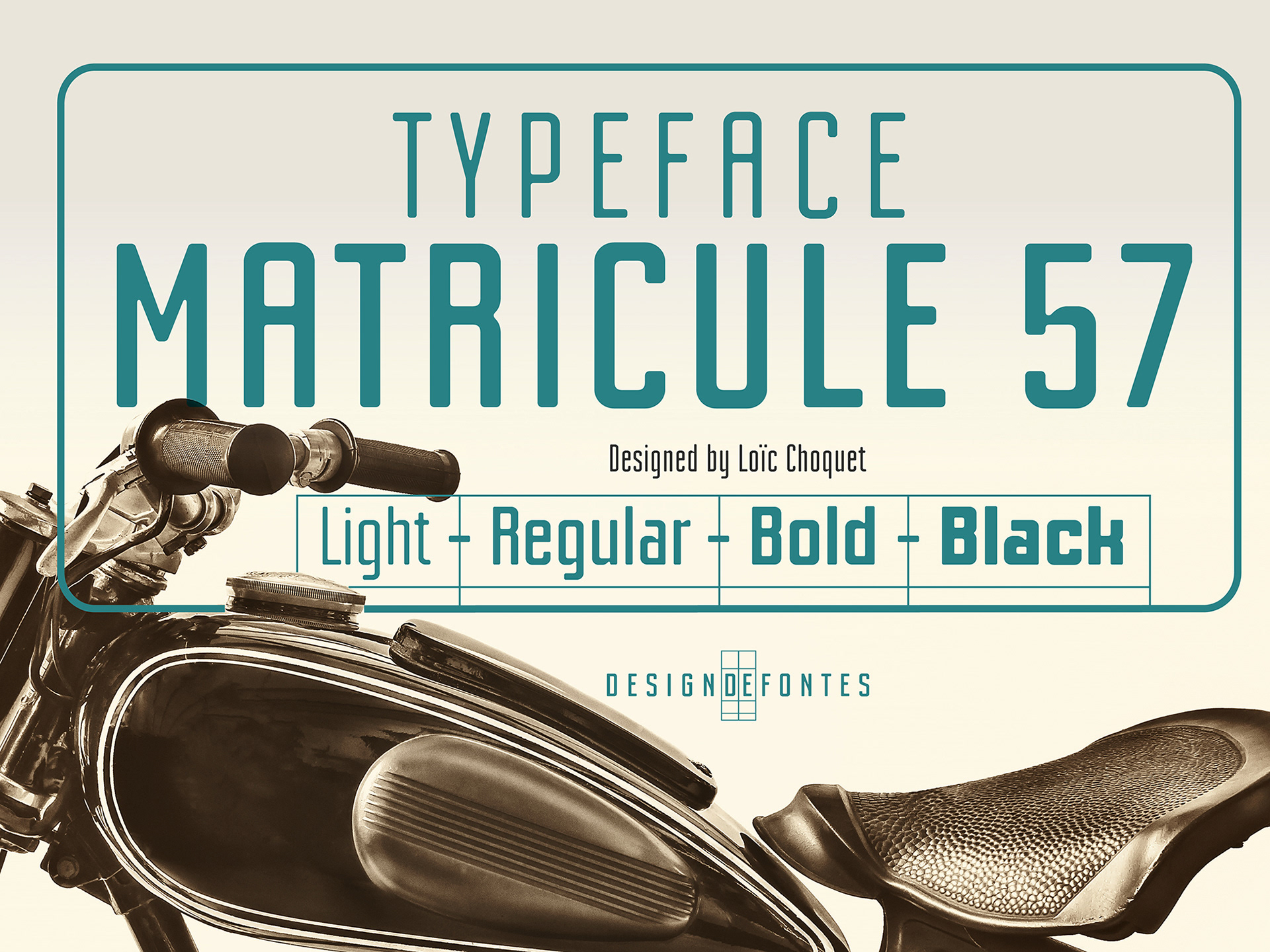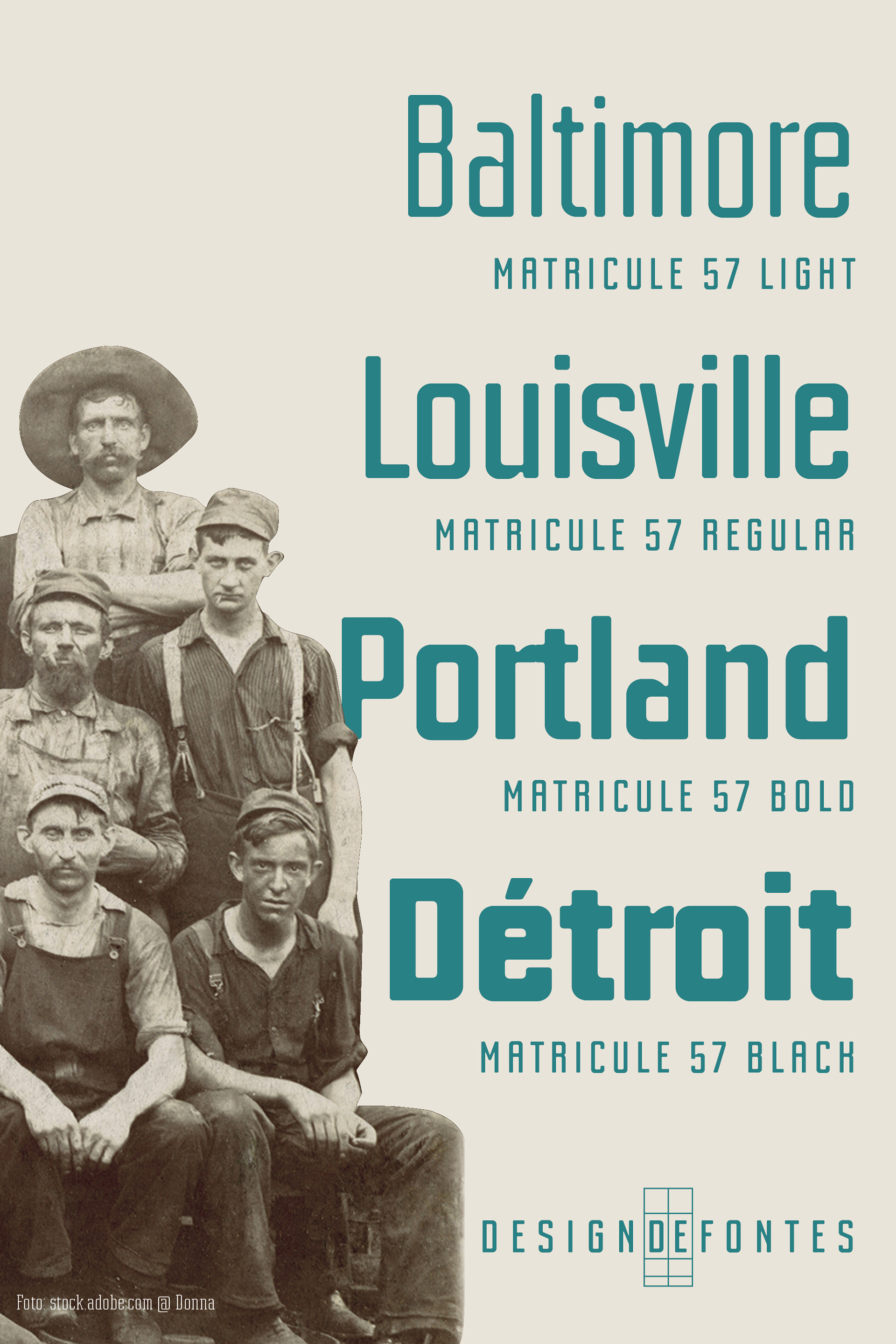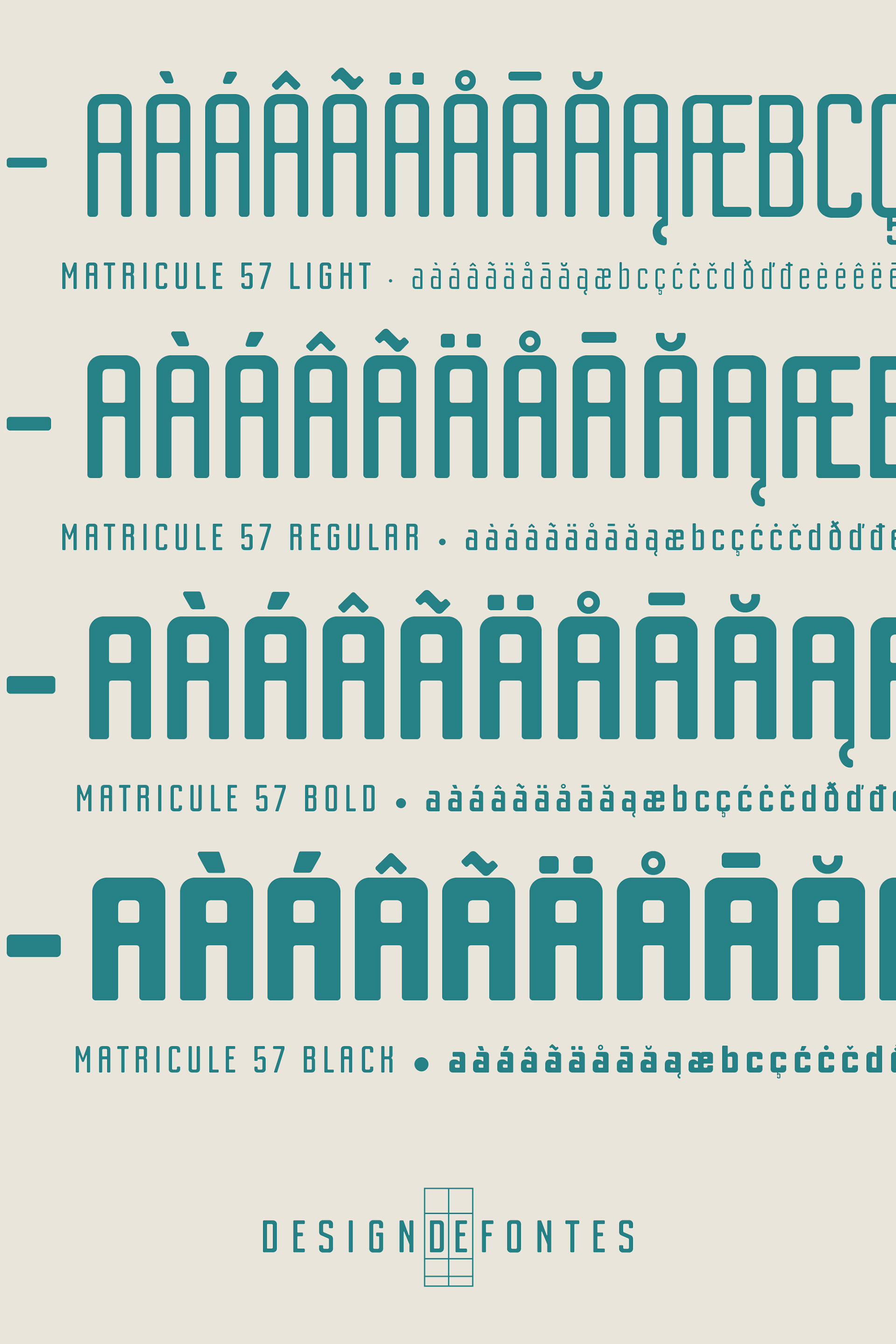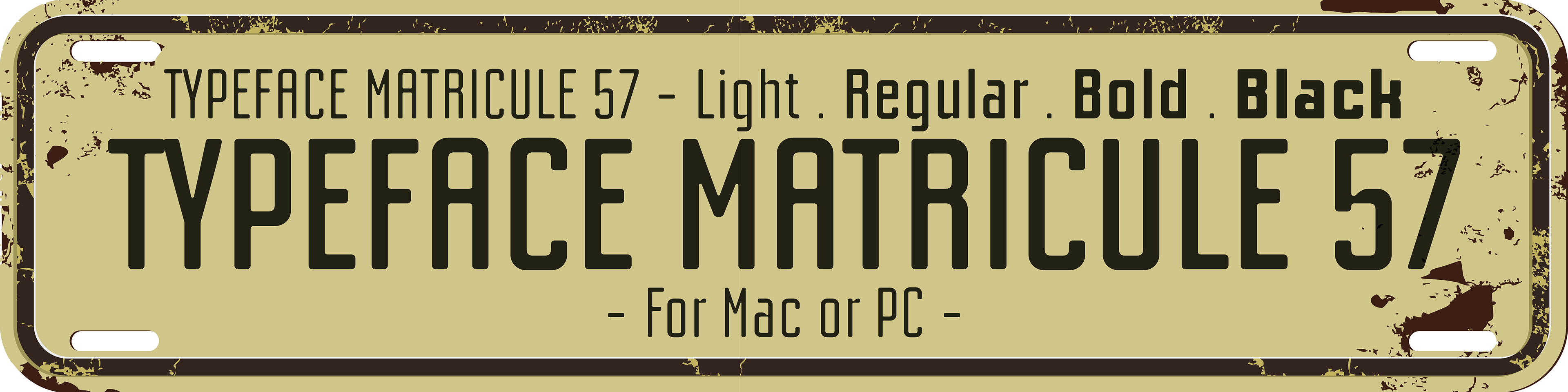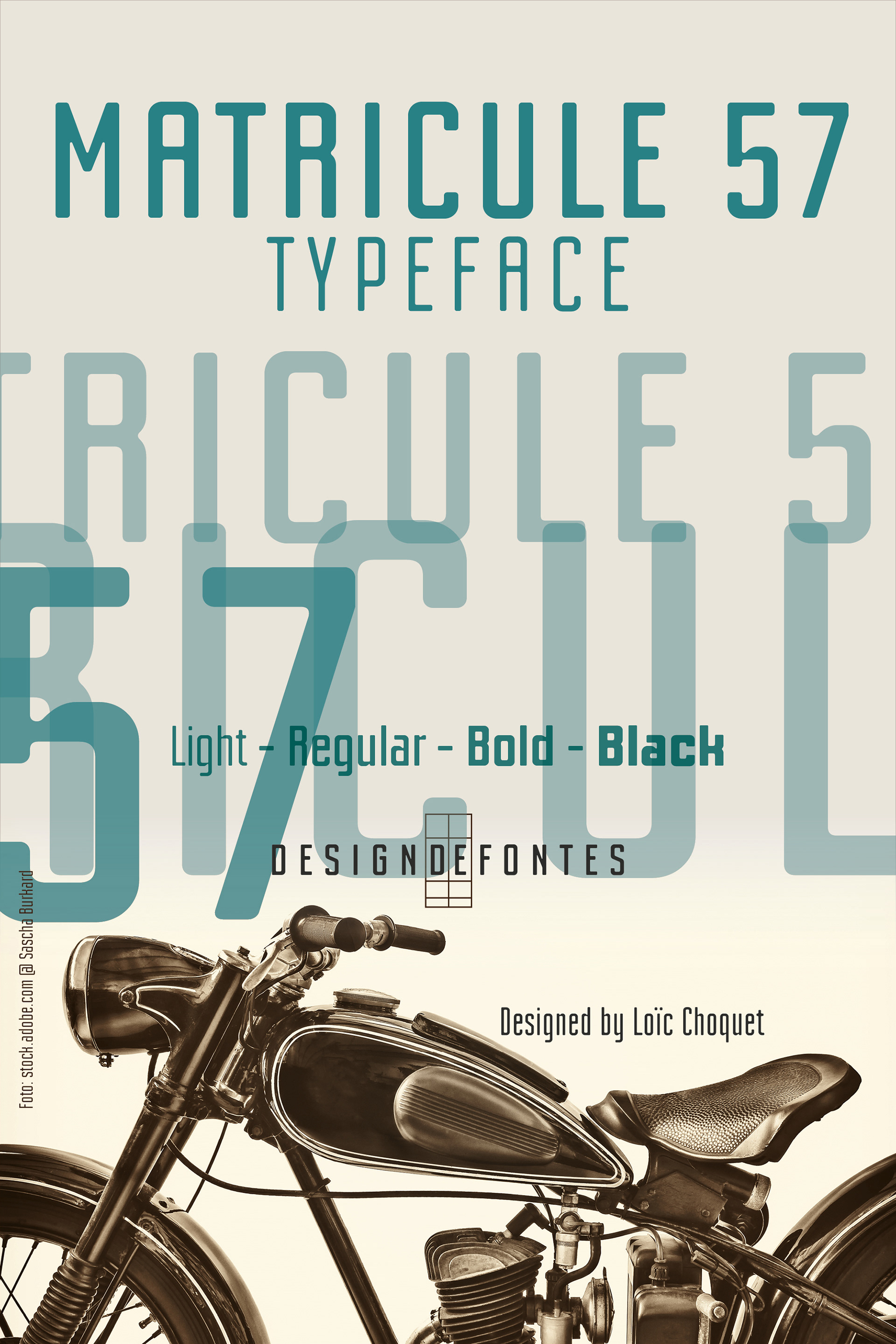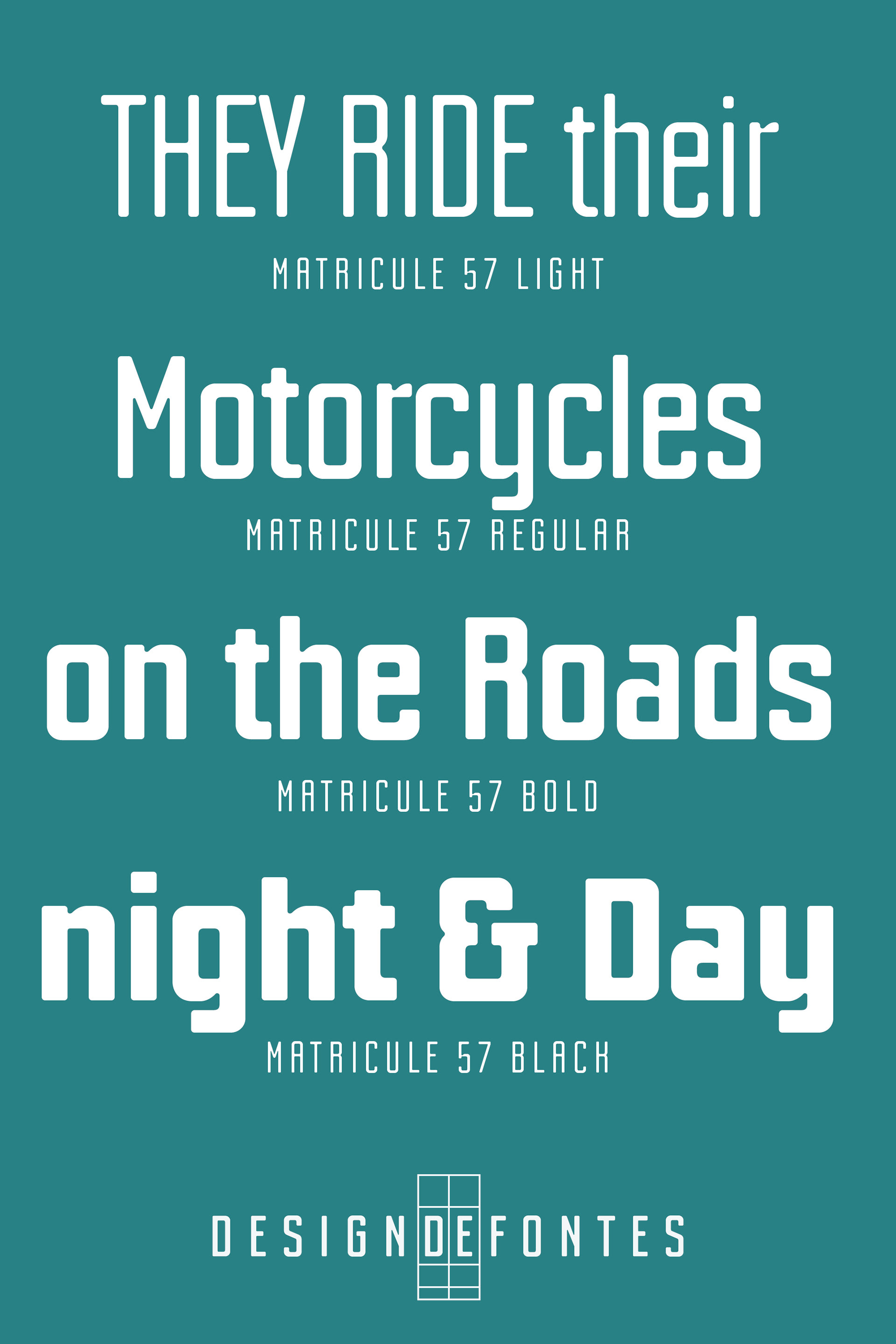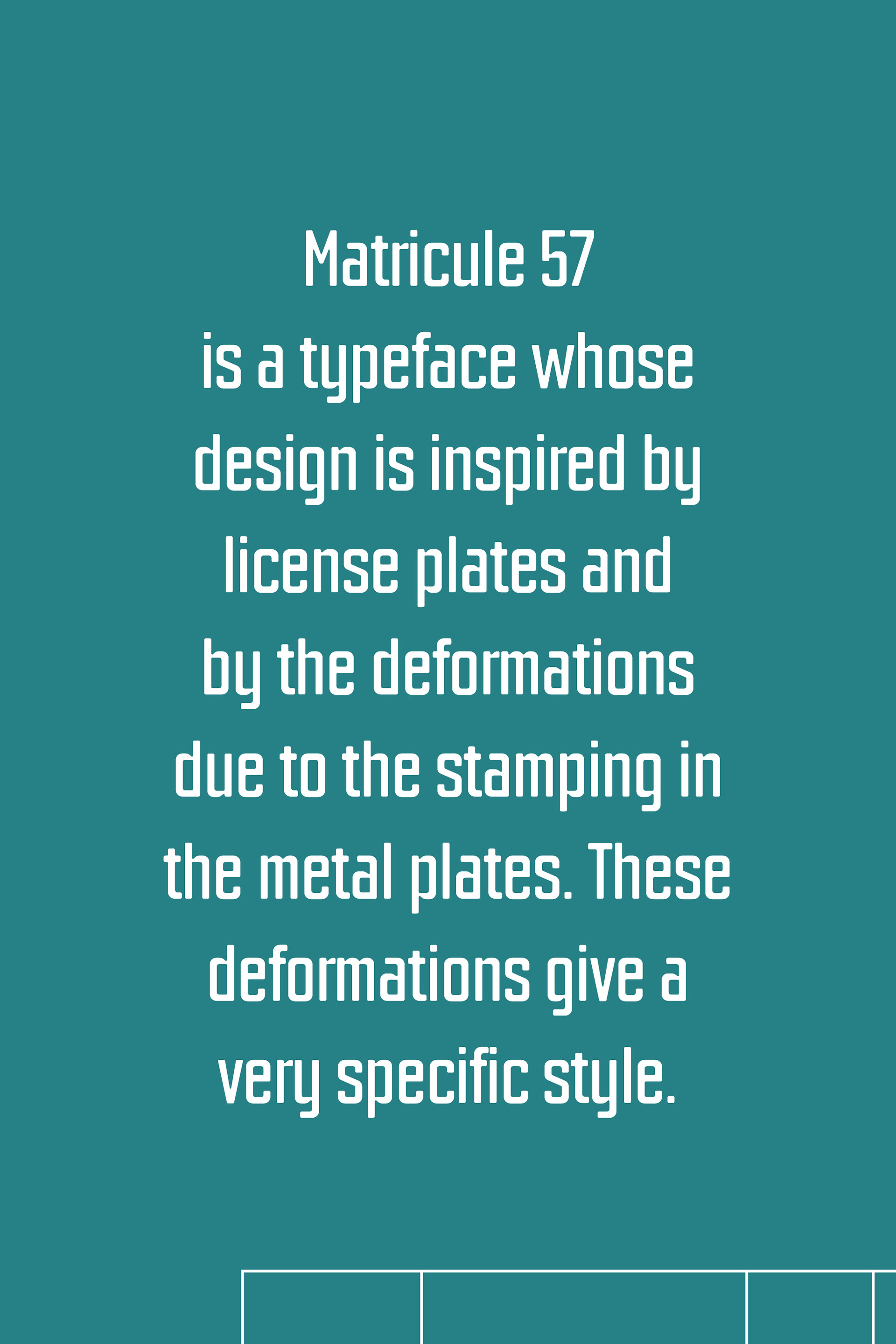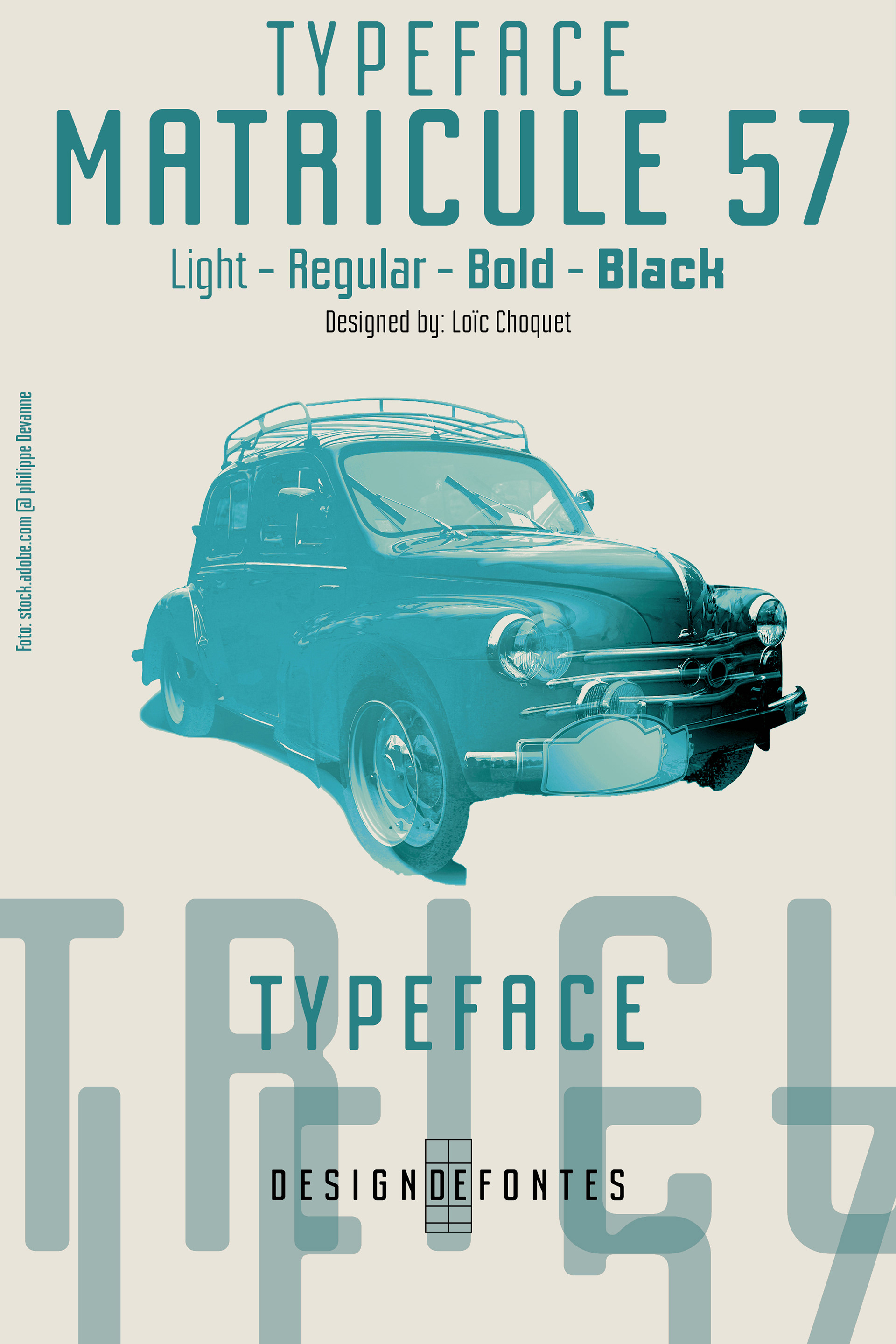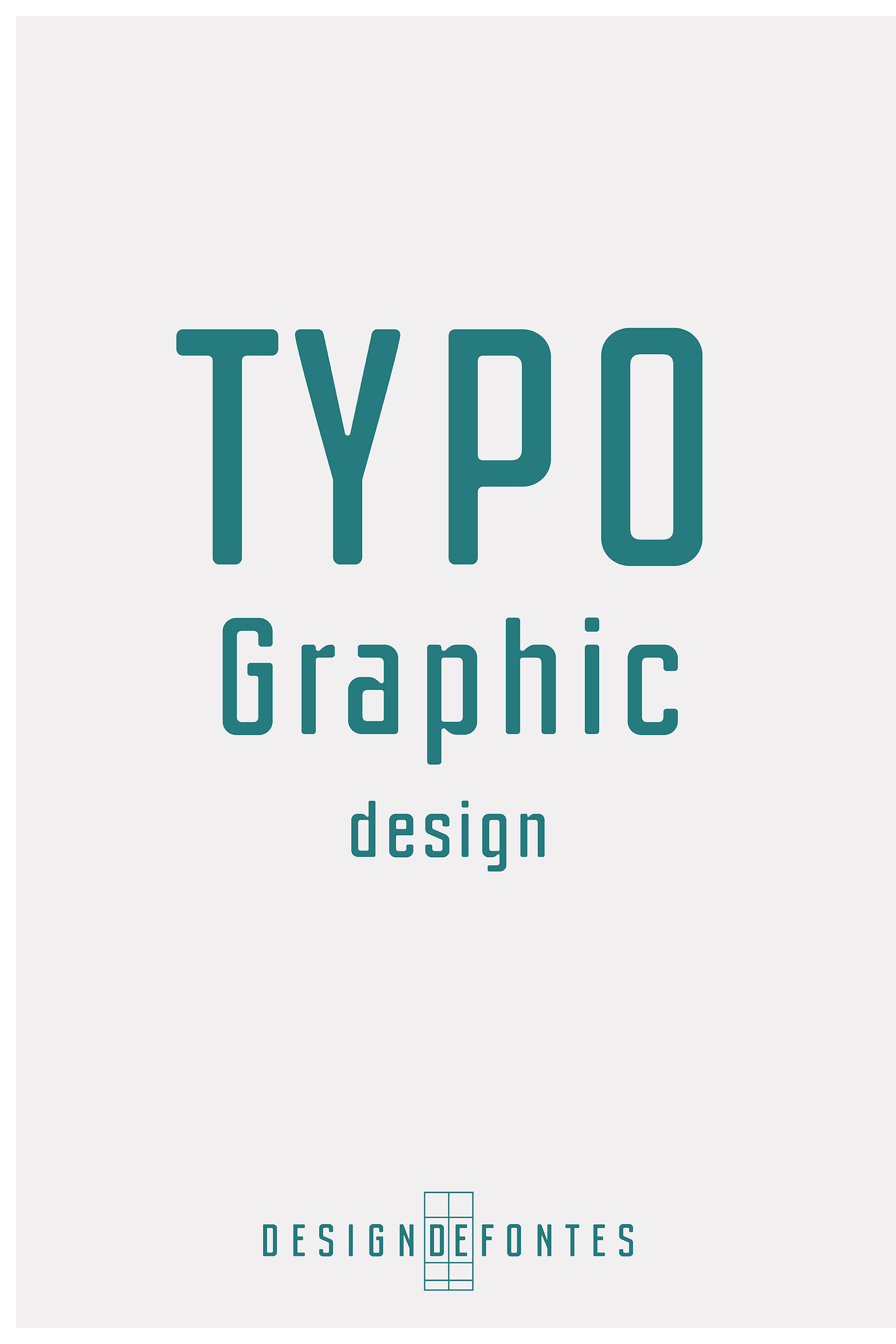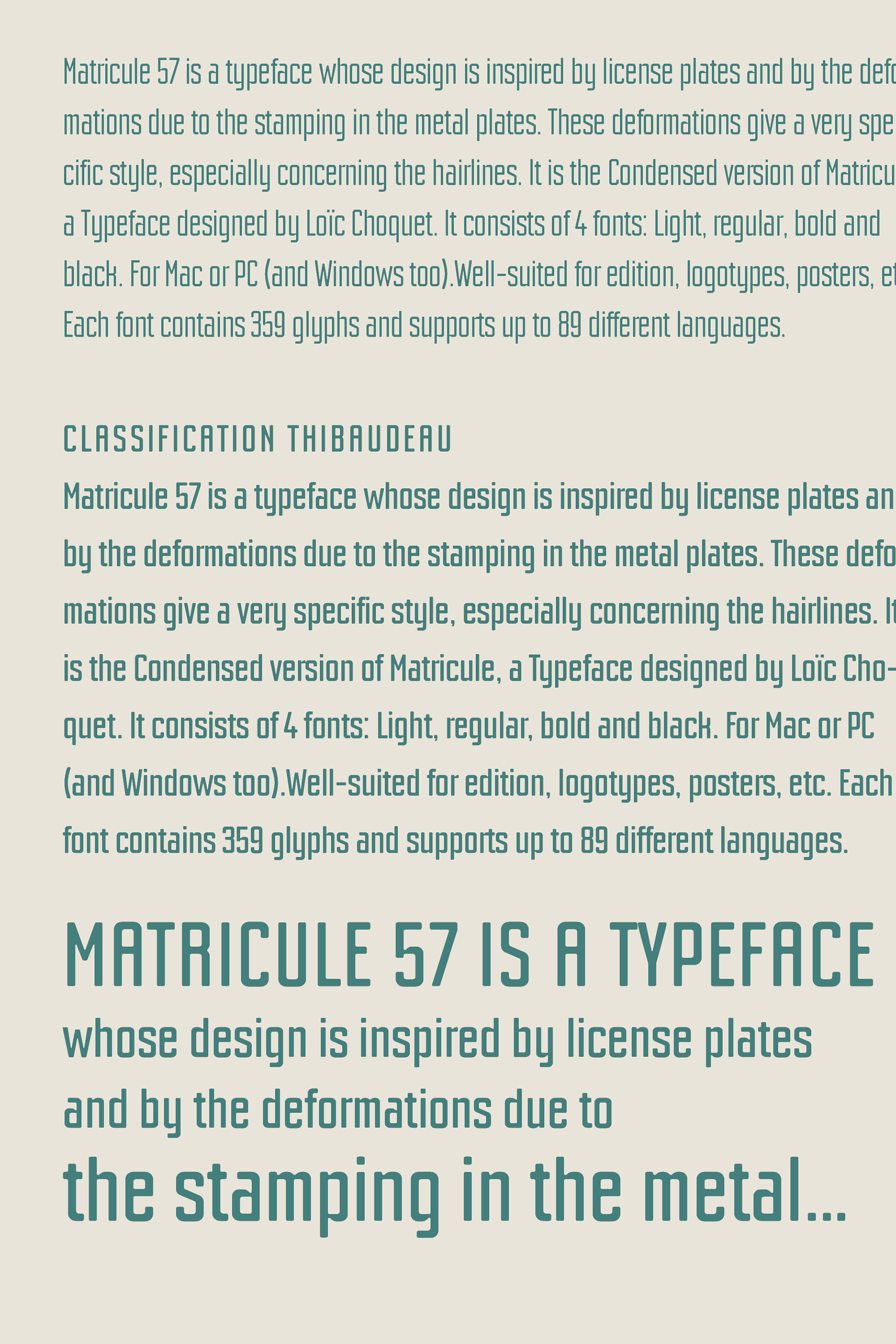
Matricule 57
Création de caractère typographique
(Loïc Choquet pour designdefontes, ma fonderie)
Matricule 57 est un caractère dont le design et inspiré par les plaques d’immatriculations et plus particulièrement par les déformations provoquées par la pression des caractères dans les plaques métalliques. Ces déformations donnent aux caractères un style spécifique notamment concernant les déliés de liaisons de ces caractères.
Matricule 57 est la version condensée de Matricule, un caractère dessiné par Loïc Choquet.
Matricule 57 est composé de 4 fontes : light, regular, bold et black.
Matricule 57 est prête à l’emploi pour 89 langues différentes